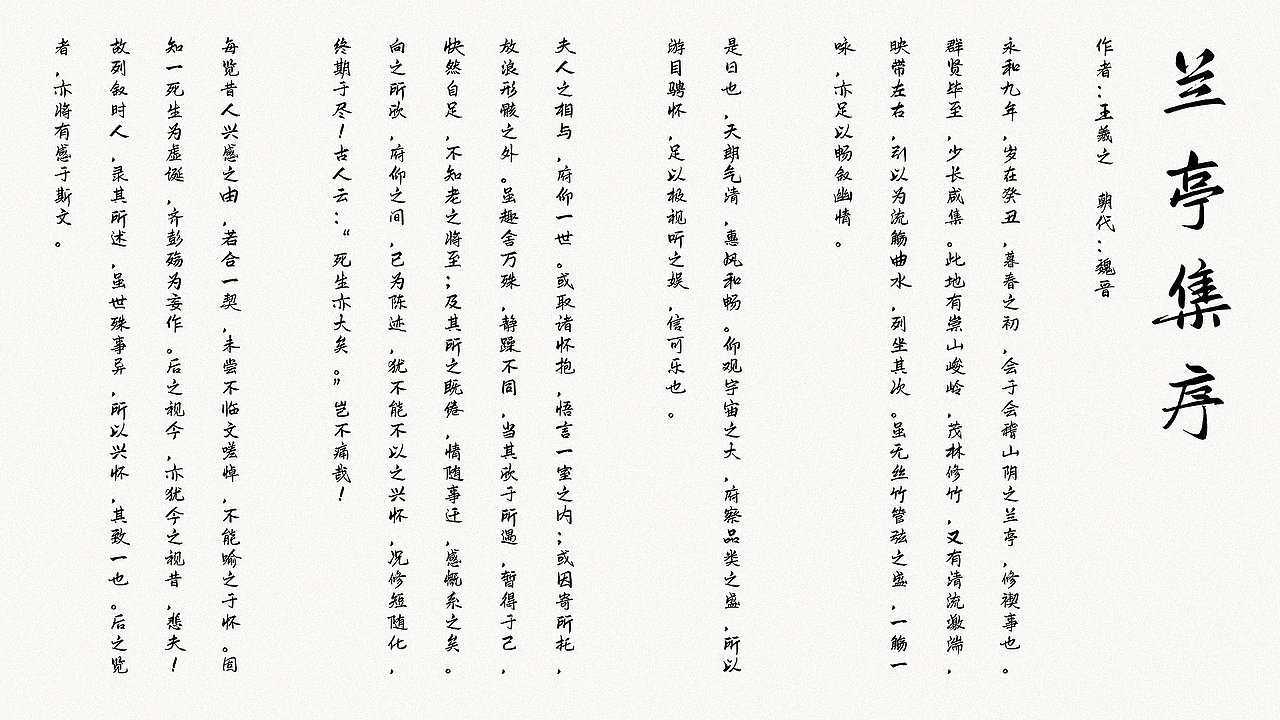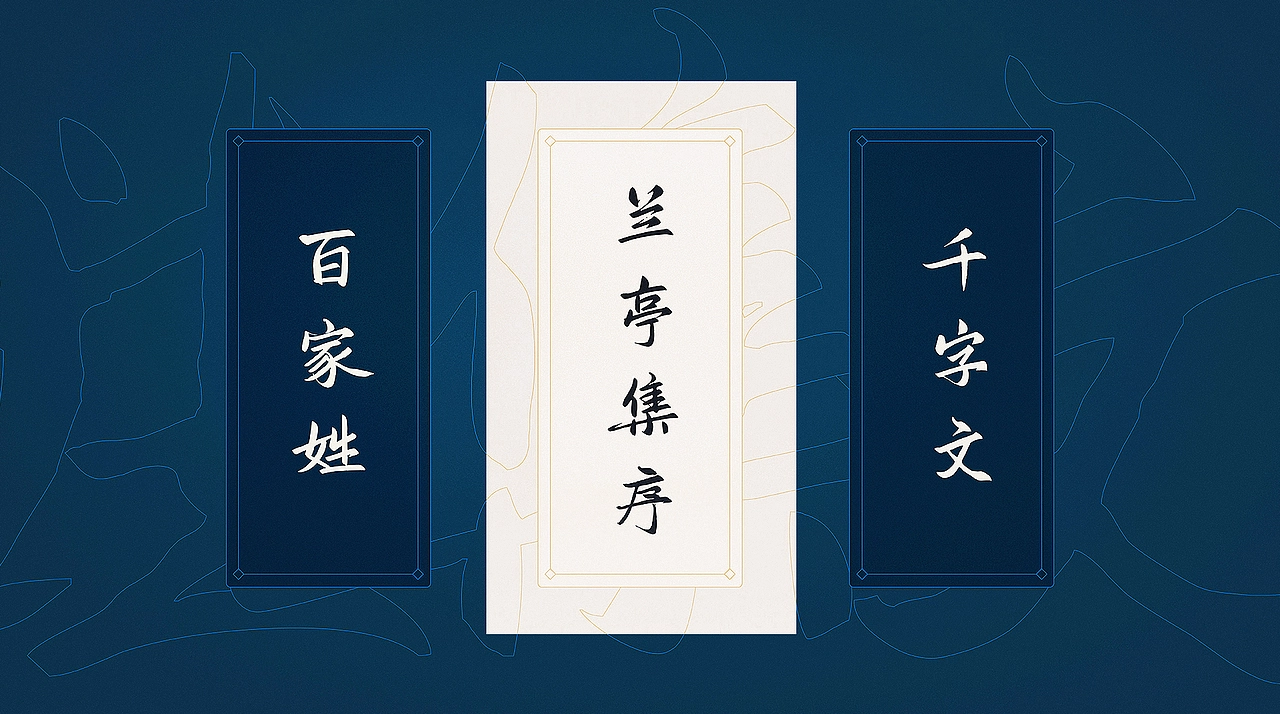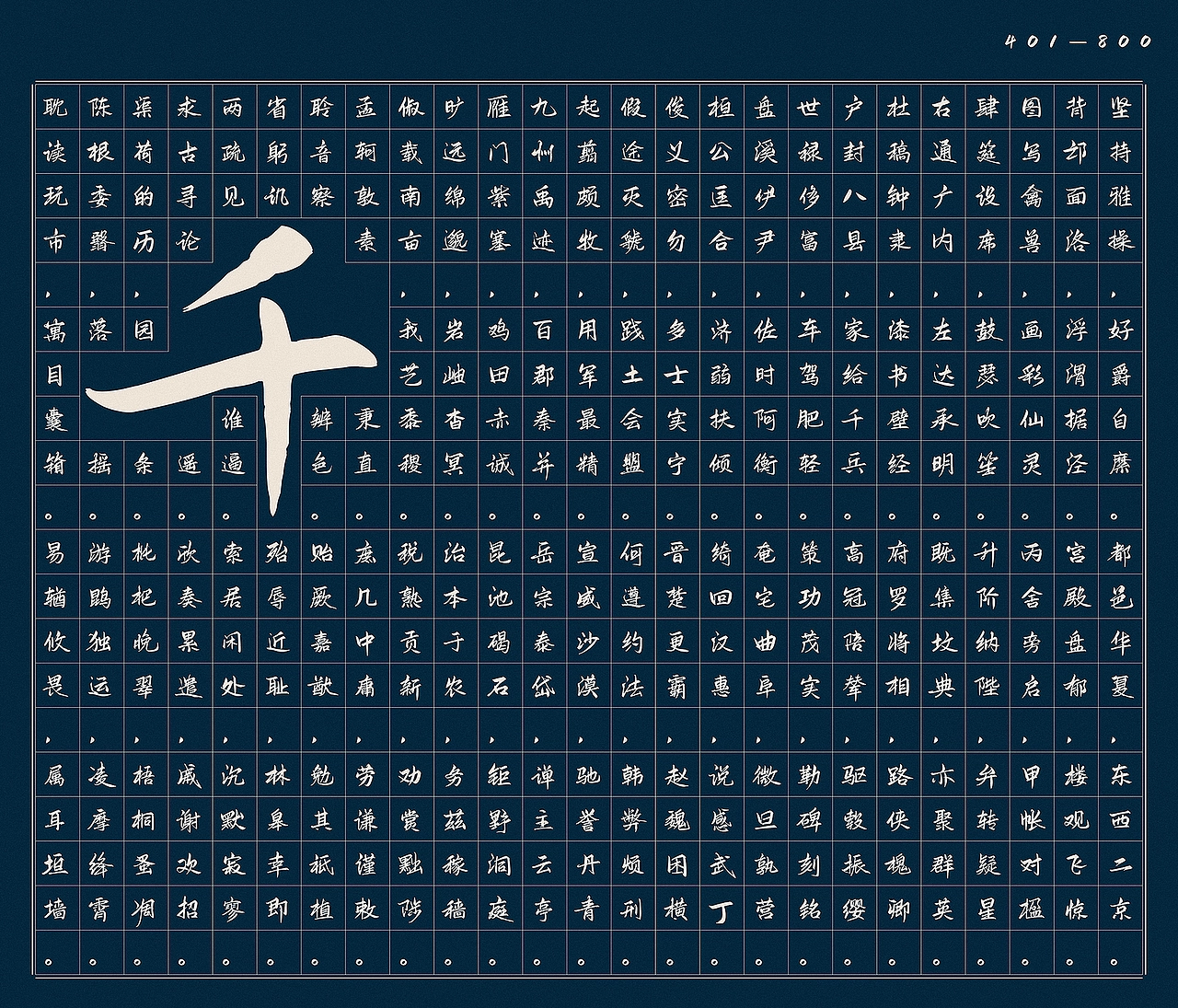
鸿雷板书简体最初是设计师鸿雷老师练字时候抄写的千字文,因为已经抄写了1000多字,距离最基本的字体成型也就差五六千字了,所以就萌生出了制作这套字体。之所以叫鸿雷板书简体则是由于这套字全是他一笔一划用手绘板写的简体部分。
虽然是手写体,但鸿雷板书简体字形端庄大方,中宫设计适中,字体重心稳定,即使在较长的文案中排版也非常简洁整体,不会让人觉得眼花缭乱,这在手写体里也是很难能可贵的,因此在 2020 年 4 月一经发布就受到广泛好评。